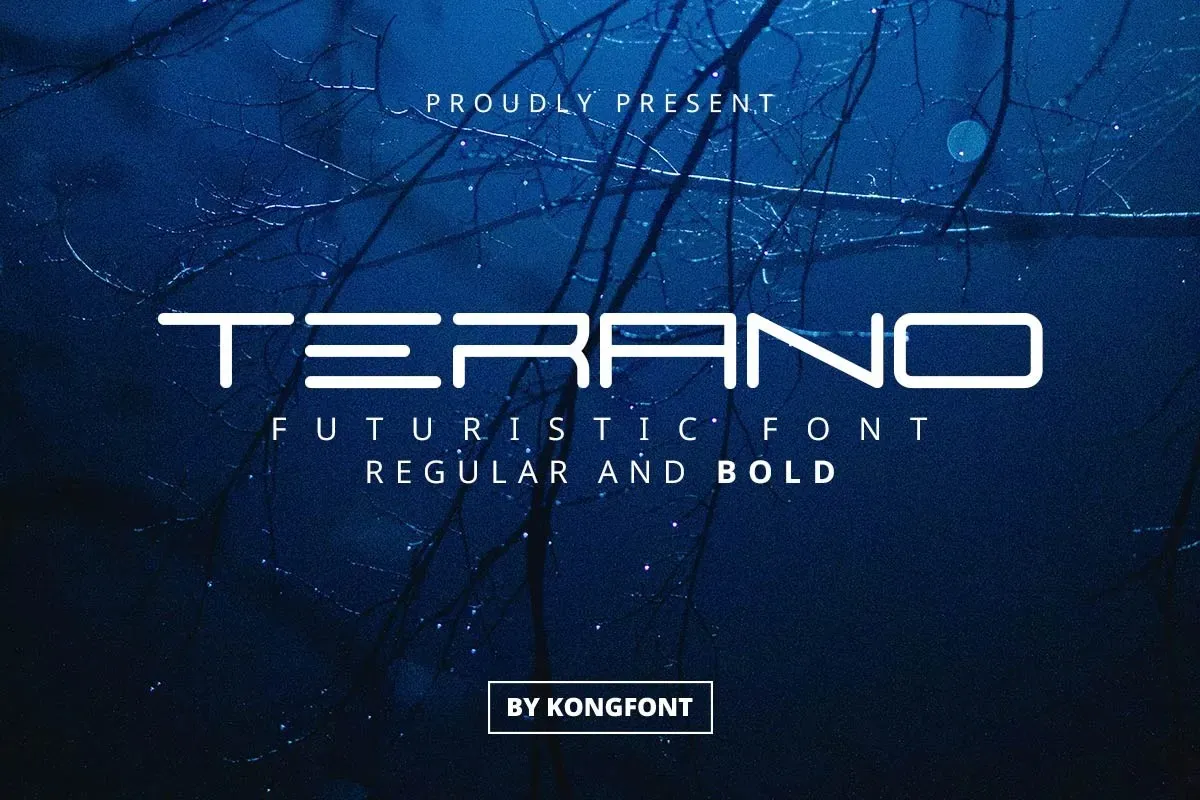
Terano Font
A Terano Font é uma elegante tipografia de destaque com duas opções estilizadas perfeitas para a criação de identidades visuais e logos. Suas linhas retas e robustas se destacam como uma escolha ideal para projetos de branding, logomarcas, letras gráficas, logotipos, roupas, panfletos, embalagens, materiais promocionais e arte fílmica. Esta fonte é perfeita para qualquer projeto visual que exija um estilo moderno e sofisticado, seja ele uma camiseta de moda casual ou a capa de um livro exclusivo. Composta para se adaptar à diversas necessidades de design, a Terano Font oferece uma versatilidade que complementará com perfeição os seus projetos mais criativos.